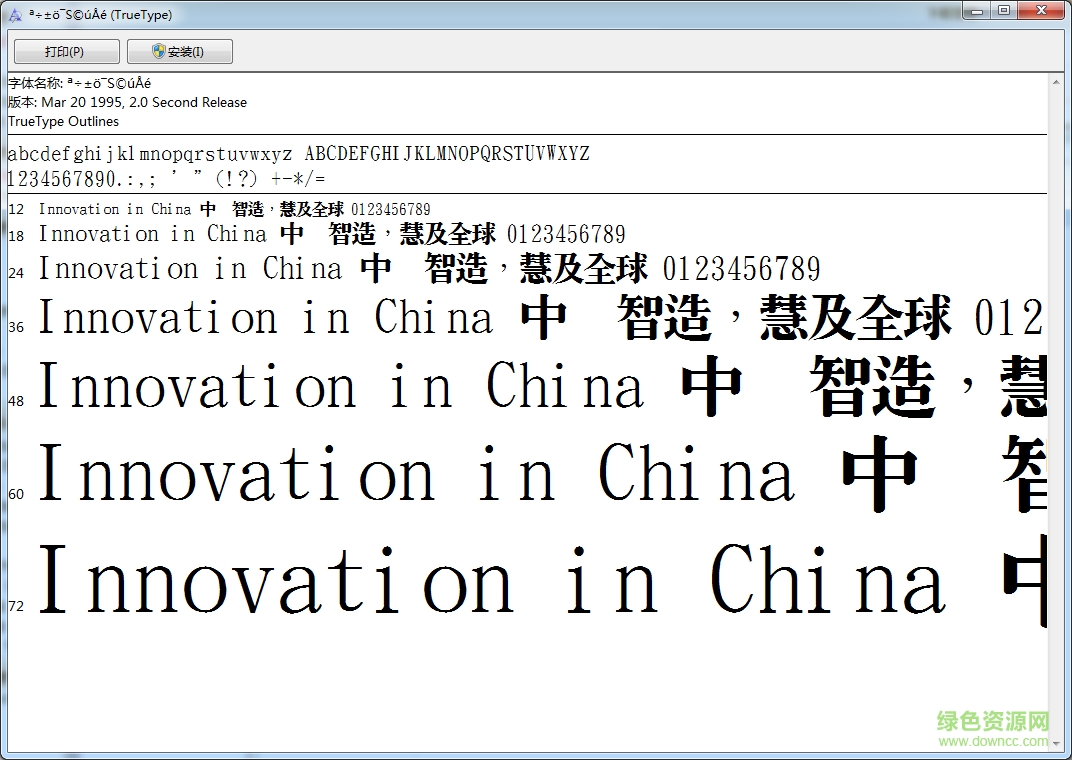
金梅特明體是一個(gè)電腦字體軟件,有些時(shí)候需要用到這樣的字體,簡潔清秀,非常有個(gè)性十分美觀,需要的朋友快來下載吧。歡迎來綠色資源網(wǎng)下載!
金梅特明原體國際碼字體是一款用于產(chǎn)品設(shè)計(jì)方面的字體,本作品使用于廣告設(shè)計(jì)字體、網(wǎng)頁設(shè)計(jì)字體、包裝設(shè)計(jì)字體、 屏幕顯示字體等,有需要的朋友下載看看吧